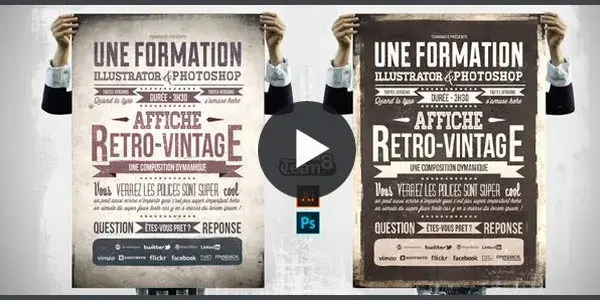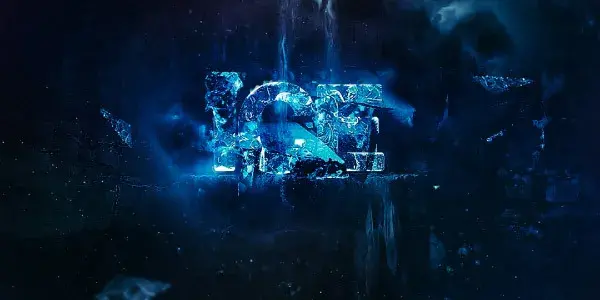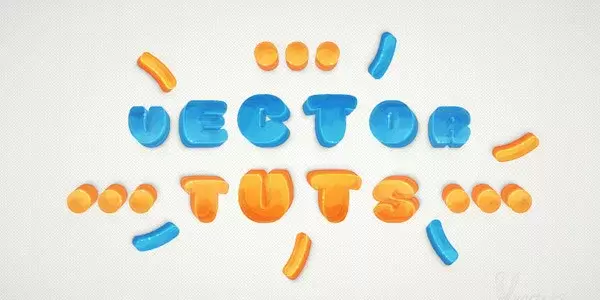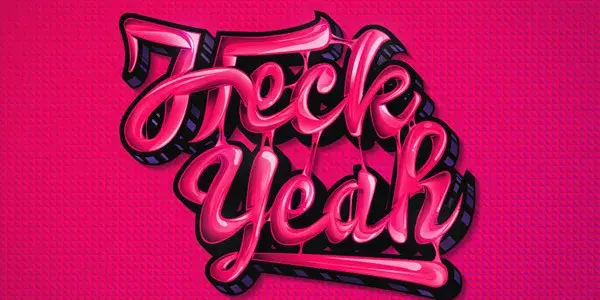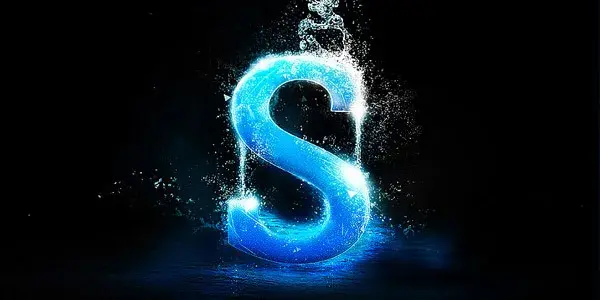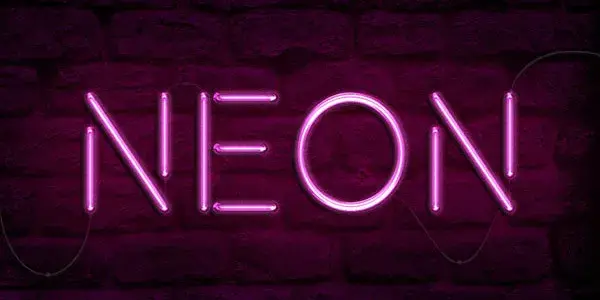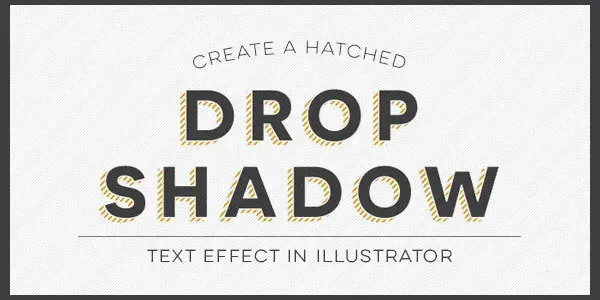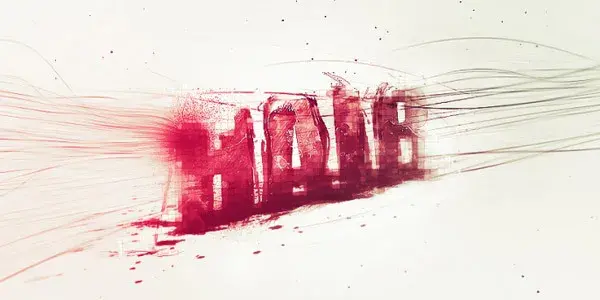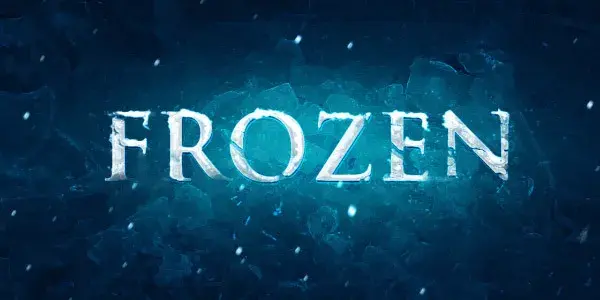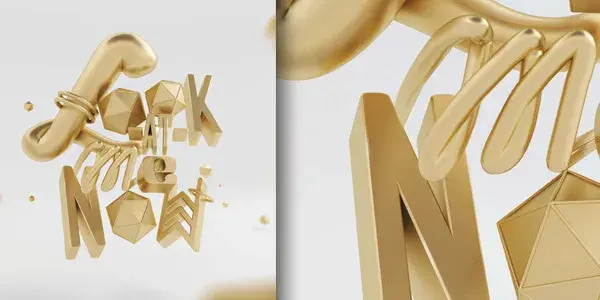
33 tutoriels pour maîtriser les effets de texte avec Photoshop et Illustrator
Nous avons réalisé une grande sélection de tutoriels pour concevoir des effets de textes originaux avec Photoshop et Illustrator, pour tous ceux qui désirent approfondir leurs compétences.
Suivre des tutoriels reste toujours intéressant, que l'on soit débutant ou confirmé, ils permettent de se perfectionner dans les outils tels que Photoshop et Illustrator et ainsi découvrir des astuces ou de nouvelles techniques.
Retrouvez dans cette sélection 33 effets de typographie avec Photoshop et Illustrator à réaliser étape par étape, certains tutoriels sont en vidéo, la plupart des liens redirigent sur des sites anglophones. Nous avons sorti une liste d'exemples pour leur qualité graphique afin de vous donner une source d'effets de texte Photoshop variés et originaux qui pourront vous servir dans vos futurs projets.
Tutoriel effet typo Photoshop avec les masques de Photoshop
Tutoriel effet texte typo avec masque photoshop
Tutoriel effet texte moderne en 3D avec Photoshop
Tutoriel Effet texte moderne en 3d
Tutoriel effet texte Gloss + Bubble Gum sous Photoshop
Tutoriel Effet texte gloss et bubble gum photoshop
Tutoriel effet typographie cassée avec Photoshop
Tutoriel Effet texte typographie cassee
Tutoriel effet typographie en terre avec Photoshop
Tutoriel effet texte Typographie en terre
Tutoriel effet texte doré sous Photoshop
Tutoriel Effet texte dore photoshop
Tutoriel effet texte en 3D été avec Photoshop
Tutoriel Effet texte 3d ete
Tutoriel effet texte réaliste pour Frozen avec Photoshop
Tutoriel Effet texte realiste frozen photoshop
Tutoriel effet texte ombre portée sous Illustrator
Tutoriel Effet texte ombre portee illustrator
Tutoriel effet texte enseigne 3D Vintage avec Illustrator, Cinema 4D et Photoshop
Tutoriel effet texte Enseigne 3d vintage illustrator
Tutoriel effet texte "The Walking Dead" sur Photoshop
Tutoriel effet texte The walking dead photoshop
Tutoriel effet texte réaliste lettres 3D dorées avec Photoshop
Tutoriel Effet texte realiste lettres 3d doree
Tutoriel effet texte gravé dans le bois avec Photoshop
Tutoriel effet Texte grave bois photoshop
Tutoriel effet typographie avec de la nourriture illustrée avec Photshop
Tutoriel effet texte Typographie nourriture illustree
Tutoriel effet typo rapido avec Photoshop
Tutoriel effet texte Typo rapido
Tutoriel effet texte affiche Rétro / Vintage avec Illustrator
Tutoriel effet texte Affiche retro vintage illustrator
Tutoriel effet texte "Fun Wiener" avec Illustrator
Tutoriel Effet texte fun wiener illustrator
Tutoriel effet texte Néon réaliste Photoshop
Tutoriel Effet texte neon realiste photoshop
Tutoriel effet texte à base d'eau sous Photoshop
Tutoriel Effet texte impressionnant base eau photoshop
Tutoriel effet texte avec l'outil Plume et Pinceau dans Photoshop
Tutoriel Effet texte outil plume pinceau photoshop
Tutoriel effet de texte La reine des neige dans Photoshop
Tutoriel Effet texte reine des neiges photoshop
Tutoriel effet texte en nuage avec Photoshop
Tutoriel Effet texte nuage
Tutoriel effet texte Iron Man sous Photoshop
Tutoriel effet texte Iron man photoshop
Tutoriel effet de texte 3D Retro avec Photoshop
Tutoriel Effet texte 3d retro
Tutoriel effet texte "Royal" avec Photoshop
Tutoriel effet texte Royale 3d texte photoshop
Tutoriel effet typographie illustrée en fromage sous Illustrator
Tutoriel effet texte Typographie illustree fromage illustrator
Tutoriel effet texte électrique dans Illustrator
Tutoriel Effet texte electrique illustrator
Tutoriel effet de texte sur une texture bois avec Photoshop
Tutoriel Effet texte texture bois
Tutoriel effet typographie avec du lait dans Photoshop
Tutoriel Effet texte typographie lait photoshop
Tutoriel bannière personnalisée en texte 3D avec Photoshop
Tutoriel effet texte Realiser banniere personnalisee texte 3d
Tutoriel effet texte Retro, 3D et texturé dans Photoshop
Tutoriel Effet texte retro 3d texture photoshop
Tutoriel effet texte semi-transparent avec Illustrator
Tutoriel effet texte Creer effet semi transparent illustrator
Tutoriel effet texte glace dans Photoshop
Tutoriel effet texte Creer effet glace texte photoshop